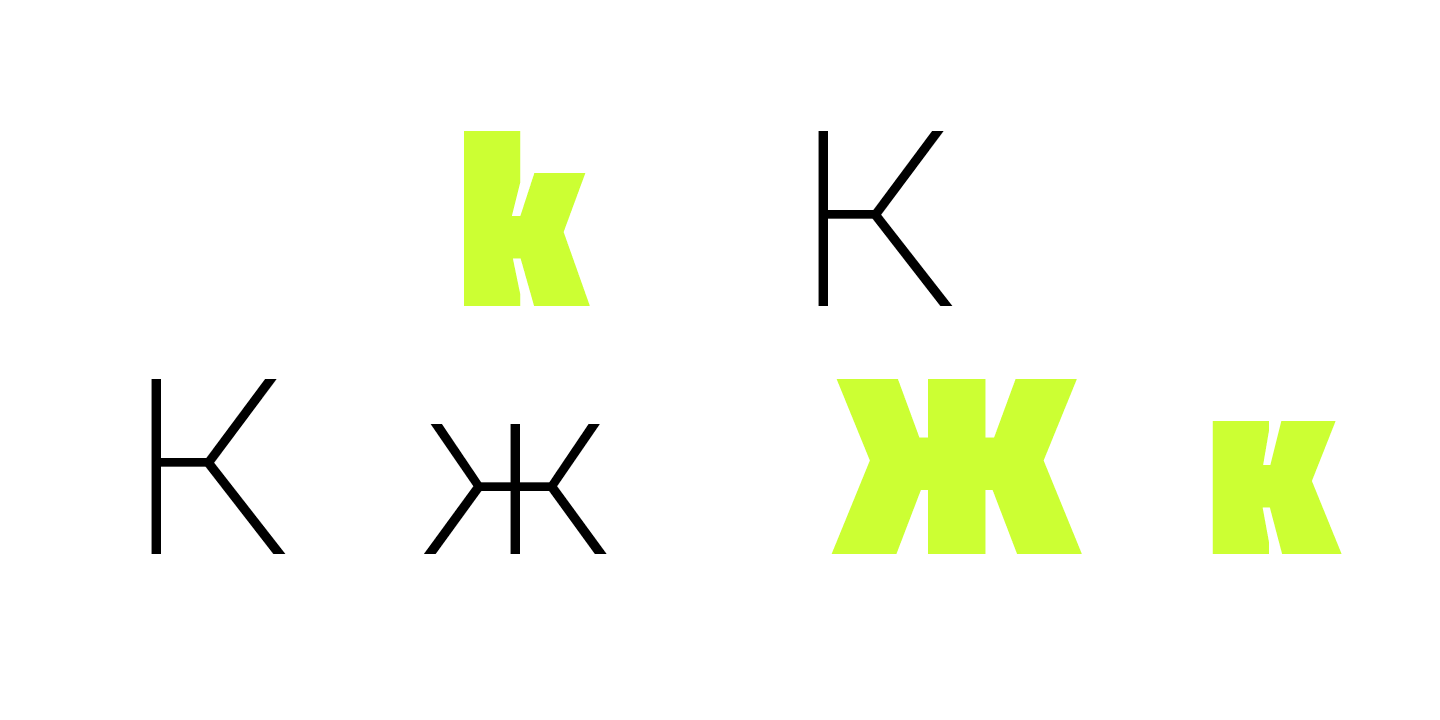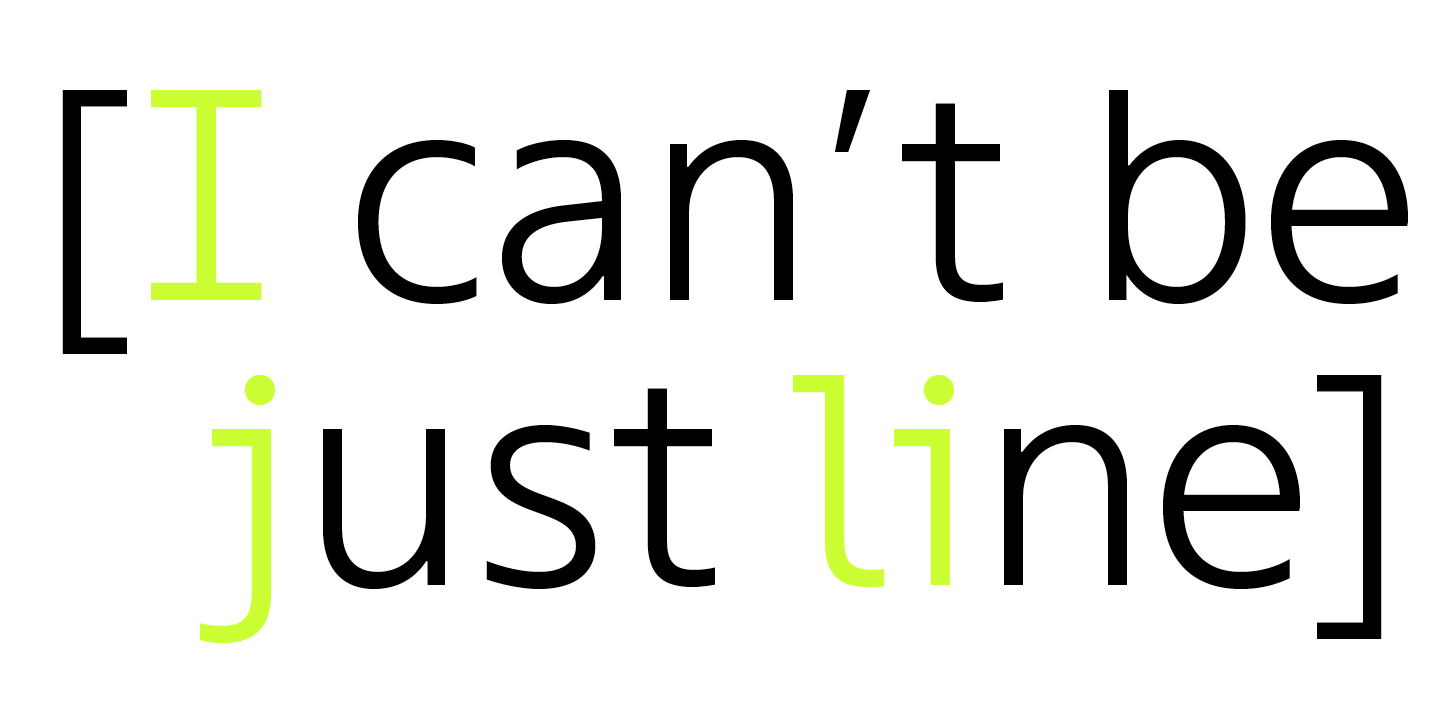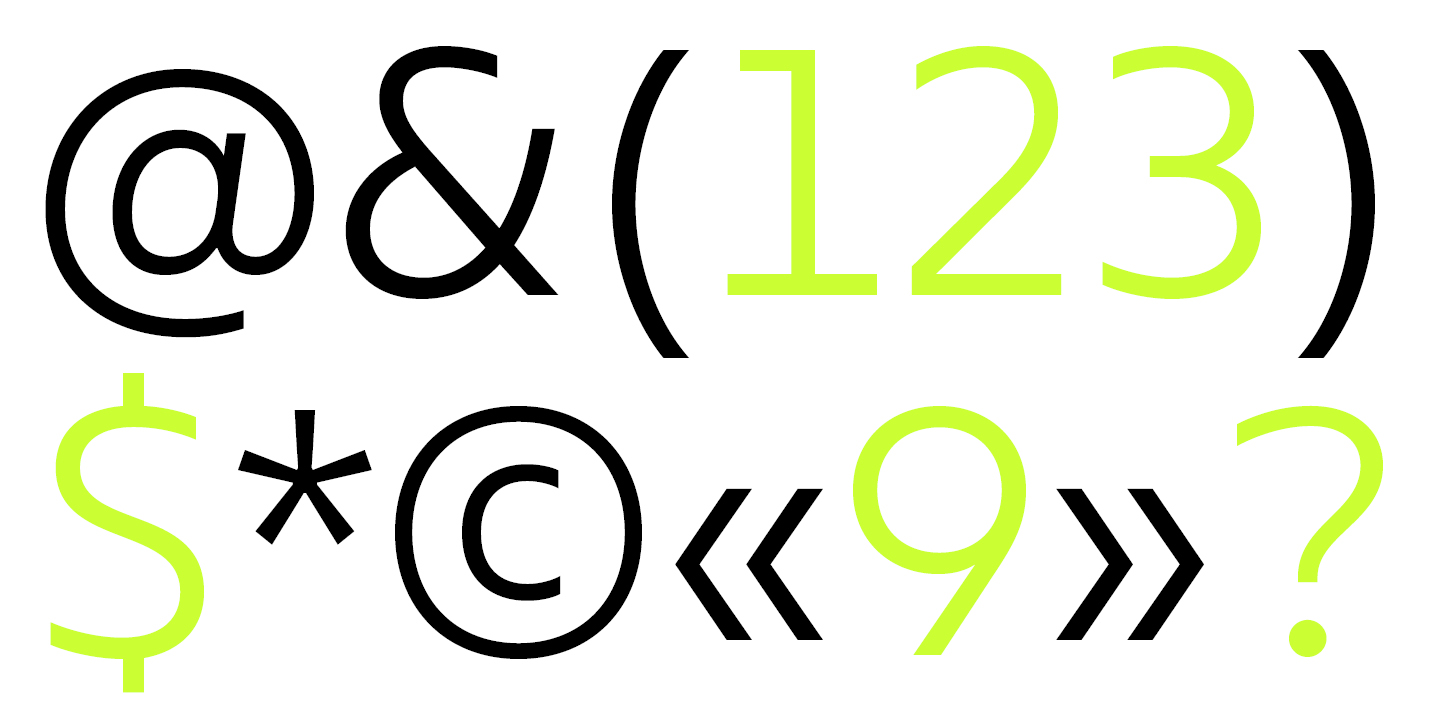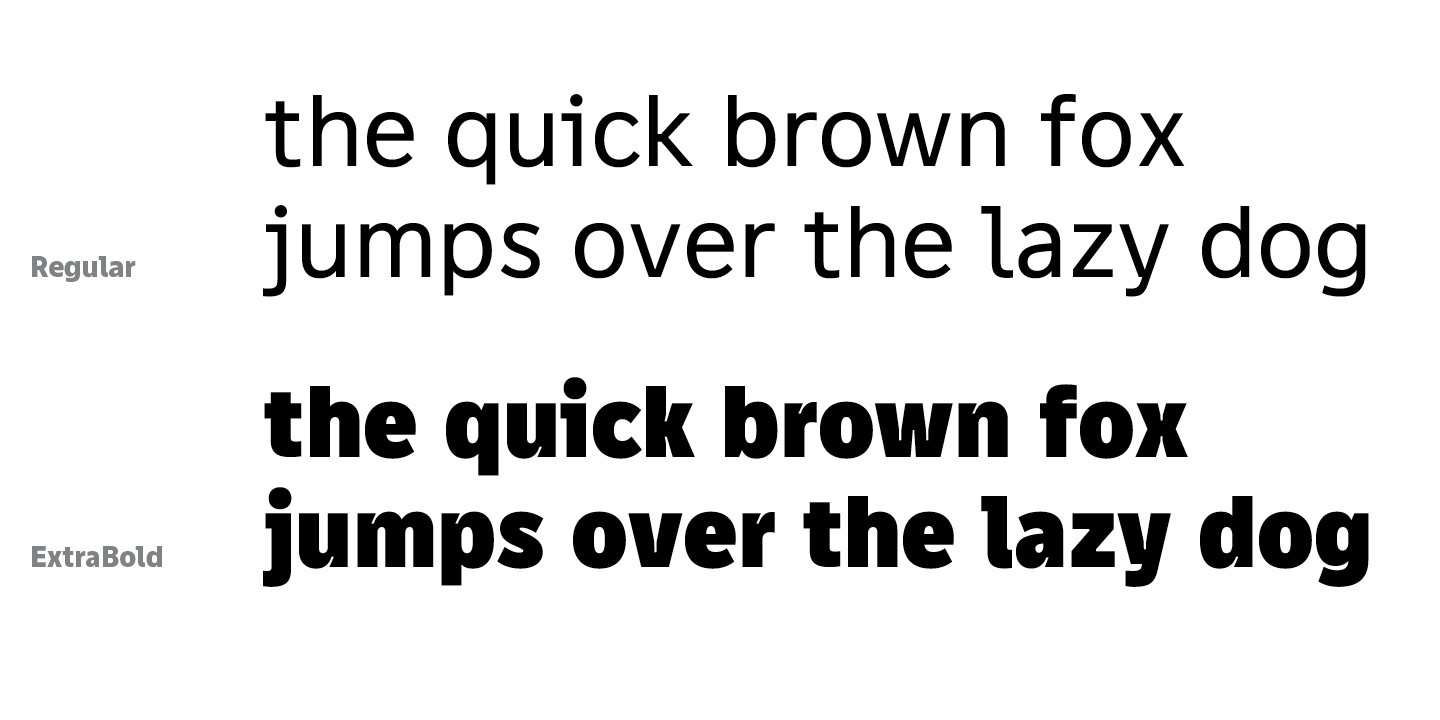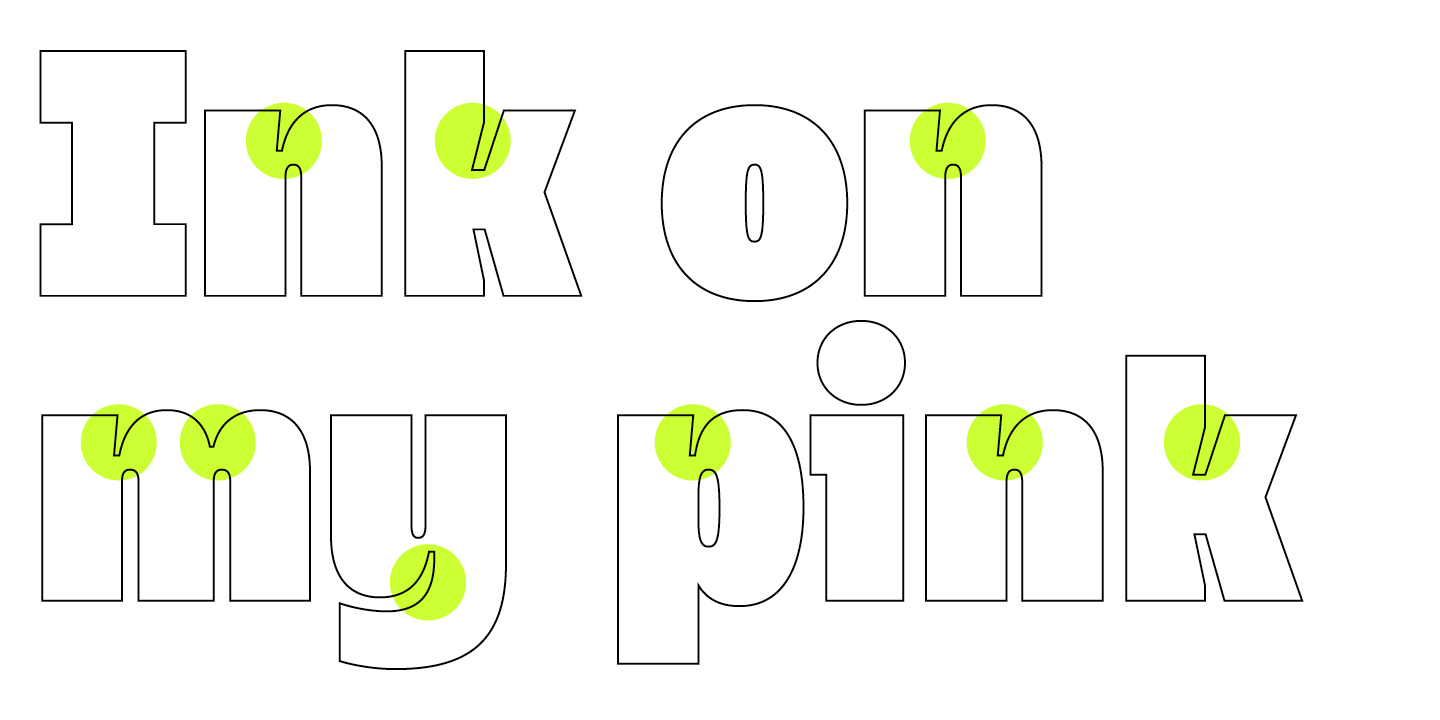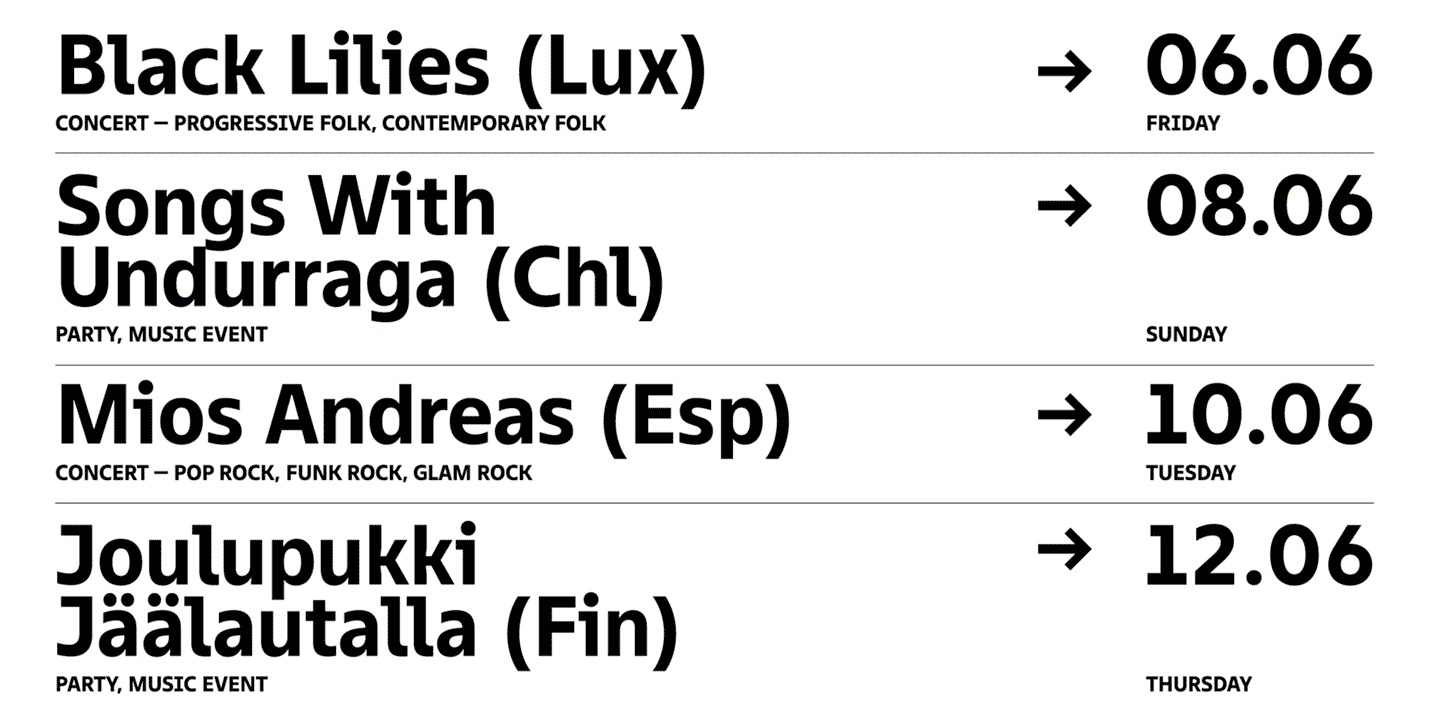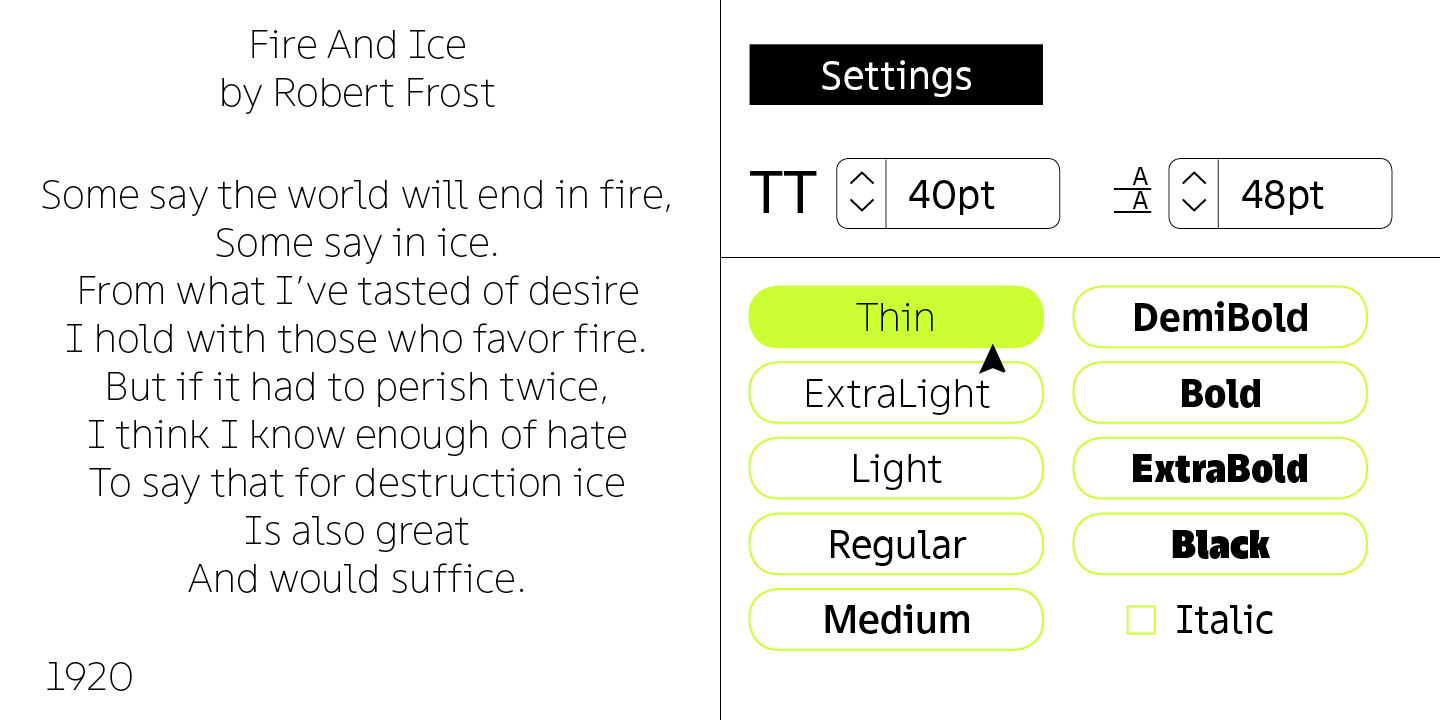
Менять начертания, сохраняя макет — открываем тайны создания униширинного шрифта TT Fellows
В январе 2022 года на площадки вышла новая шрифтовая гарнитура TypeType — TT Fellows. Практически сразу она привлекла внимание дизайнеров со всего мира, что неудивительно, ведь универсальный, лаконичный и функциональный шрифт подойдёт для большинства современных проектов.
Шрифт, который не испортит вёрстку, если захочется поменять толщину в процессе работы. Дружелюбный по графике, интуитивный в использовании. Пользоваться TT Fellows безопасно и приятно. В знаковом составе нет ничего лишнего, обширная поддержка языков, которых достаточно для широкого использования в самых разных задачах. Полезные фичи, функциональные лигатуры.
Несмотря на нейтральный характер, в зависимости от целей, гарнитура может проявить совершенно разное настроение: как мягкое и спокойное, так яркое или даже брутальное.
Добавьте сюда факт, что TT Fellows — первый униширинный шрифт в коллекции TypeType, и станет понятно, что у такой гарнитуры не было шансов остаться незамеченной.
Заинтригованы? Давайте мы расскажем о новом шрифте подробнее.
Униширинность
Когда новый шрифт был на этапе идеи, мы понимали только одно: коллекции шрифтовых гарнитур TypeType нужен ещё один нейтральный гротеск. Как TT Norms® Pro, TT Commons™ Pro или TT Hoves, то есть функциональный и покрывающий максимальную область применения. Такие гарнитуры популярны и удобны, современны и практичны.
Униширинность
Однако делать аналогичный уже выпущенным шрифтам проект казалось не самой интересной задачей. Все вышеперечисленные гарнитуры — геометрические гротески, поэтому для нового шрифта мы решили сменить стиль. Геометрия по-прежнему востребована и эстетична, подумали мы, но у нас в арсенале практически нет гуманистических шрифтов, а, значит, настало время это исправить.
Вообще геометрические и гуманистические гротески похожи между собой в нейтральности и универсальности использования. Отличие в том, что геометрические гротески не обладают ярким характером, форма знаков в этих шрифтах состоит из простых геометрических фигур. Обычно это неконтрастные разноширинные шрифты, в то время как гуманистические — высококонтрастные разноширинные. В гуманистических гротесках характер приобретает мягкость, появляются отсылки к засечкам.
Назвать TT Fellows полностью гуманистическим сложно: он обладает мягкими чертами, но при этом в нём есть механистические мотивы, а в регулярных начертаниях шрифт можно сравнить с нео-гротесками. Получилось что-то среднее, ведь из каждого стиля мы взяли черты, казавшиеся нам привлекательными в рамках нового проекта.
Создать нейтральный гротеск, непохожий на главные бестселлеры студии, но при этом способный составить им компанию в арсенале пользователя, — примерно так можно сформулировать первые мысли о гарнитуре. Конечно, нам также не хотелось ограничивать область применения шрифта, скорее, наоборот, было желание сделать её практически безграничной.
Униширинные шрифты — достаточно любопытная и привлекательная, но не самая распространённая категория в шрифтовом мире. В таких гарнитурах кегельная площадка не меняет свою ширину из начертания в начертание, то есть даже при увеличении жирности шрифт не становится шире, а остаётся на месте.
В классических шрифтовых гарнитурах работает так: чем толще начертание, тем шире становится шрифт. Это логично, ведь жирные начертания требуют больше пространства, но это может создавать сложности для пользователя.
Допустим, дизайнер набирает текст в макете и хочет изменить начертание в процессе работы. Увы, макет после таких манипуляций придётся дорабатывать и подстраивать под новую ширину, ведь вёрстка неизбежно слетит. Это также касается тех, кто занимается веб-дизайном. На сайтах часто используют кнопки, при наведении на которые шрифт меняет начертание, становясь жирнее. Так посетитель сайта понимает, что навёл курсор на определённую кнопку, однако в дизайне приходится подстраивать контейнер для кнопки под новую ширину текста.
Униширинность
С униширинным шрифтом подобных проблем не возникнет. Шрифт остаётся на месте, даже если поменять начертание с самого тонкого на самое жирное. Текст будет находится в своих рамках и не поменяет расположение, дизайнер может спокойно менять начертание прямо в макете, а веб-дизайнер — ставить необходимые параметры начертаний для любых кнопок, не переживая за величину контейнера.
Для дизайнеров и верстальщиков униширинный шрифт является спасением и находкой, но в шрифтовом дизайне такая гарнитура создаёт определённые проблемы, требующие компромиссных решений. О них мы расскажем позже.
Униширинность
Итак, концепция будущего шрифта сформировалась: униширинный гротеск, универсальный и нейтральный. Кстати, для команды TT Fellows стал первым униширинным шрифтом, поэтому проект стал точкой профессионального роста. Мы бросили себе вызов.